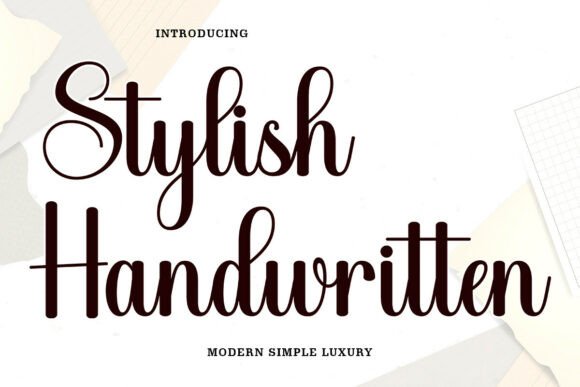
Stylish Handwritten
Une Police de Caractères Élégante et Intemporelle : En Avant-Première Plan de "Stylish Handwritten"
Pour ceux qui recherchent à la fois simplicité et sophistication dans leurs projets de design, Stylish Handwritten se positionne comme une solution incontournable. Cette police de caractères cursive écrite à la main allie chaleur humaine et élégance discrète, captivant les regards par ses traits fluides et naturels. Que vous créiez un logo, une carte de voeux ou une campagne marketing, cette police apporte une personnalité unique à chaque composition.
Pourquoi Choisir "Stylish Handwritten" ?
Les atouts de cette police sont multiples, et voici ce qui la rend particulièrement attractifve :
- Esthétique romantique et délicate : Idéal pour les projets qui exigent une touche de douceur et de nuance.
- Polyvalence incroyable : De la branding à la fashion lookbook, en passant par les cards de voeux ou les promotions commerciales.
- Émotions capturées dans chaque trait : Chaque caractère est conçu pour évoquer joie, confiance et authenticité.
Une Inspirante pour Tous les Createurs
Que vous soyez un graphiste débutant ou un designer expérimenté, Stylish Handwritten s’adapte à votre style. Son look naturel et raffiné en fait un choix inspiring